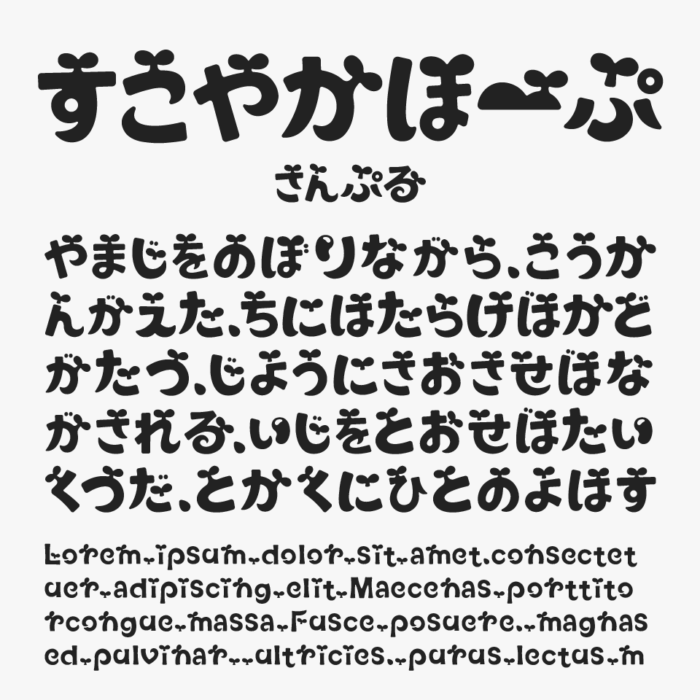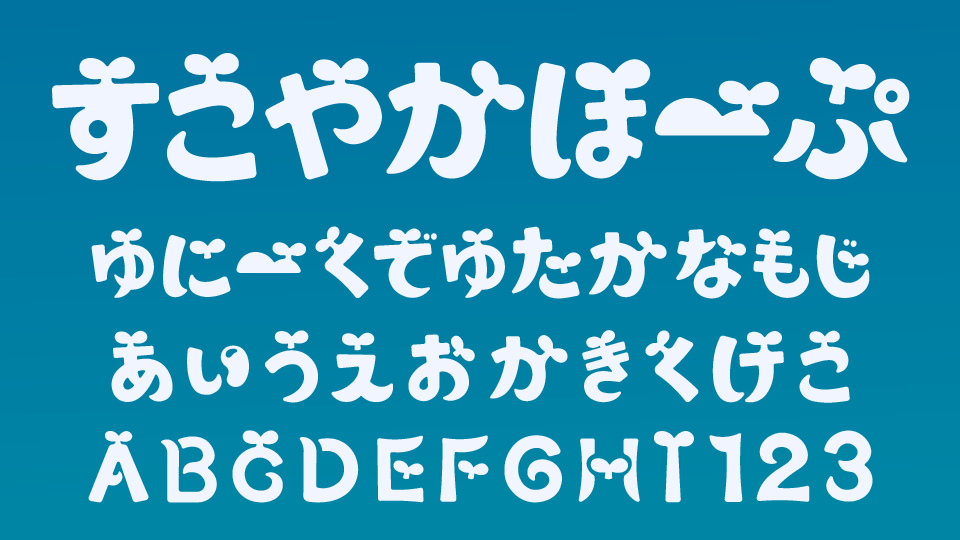
すこやかほーぷフォントは、文字の端や交差部分に双葉のモチーフを取り入れてた可愛らしいデザインフォントです。
新芽のような可愛らしい若葉が生えて、ストロークの先端が単純な丸ではなく、腫れ上がったような独特の形状をしており、見ていると愛嬌とともに不思議な中毒性を感じるデザインです。
収録文字は、ひらがな・カタカナ・アルファベット・数字・記号が収録されています。